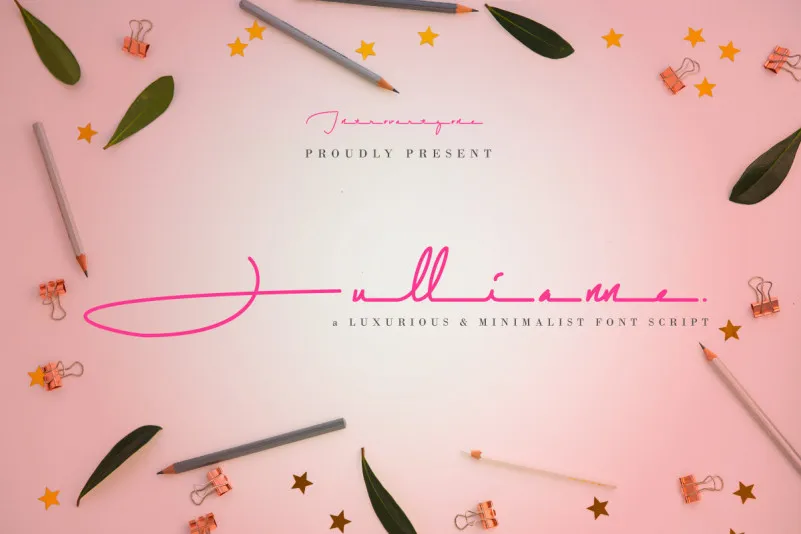
Jullianne Script Font – Download Grátis
A fonte Jullianne Script é uma combinação encantadora e minimalista para seus projetos digitais. Suavemente luxuosa e marcada por sua elegância monolineária, esta font é perfeitamente adaptada a um amplo espectro de aplicações designísticas. Ideal tanto para os designers que querem dar um toque pessoal em suas marcas como também para aqueles que precisam de um design minimalista para invocar uma atmosfera elegante e sofisticada. Este conjunto não apenas é versátil, mas também pode ser usado em várias situações, desde criação de convites para casamentos e design gráfico até a produção digital. É uma escolha perfeita para qualquer designer que deseja adicionar um toque único às suas criações, seja através do uso como marca d’água ou da criação de cartões de visitas personalizados. Seja você um artista digitais, designer gráfico ou criador de conteúdo online buscando dar um novo tom à sua identidade visual, Jullianne Script pode ser a fonte perfeita para atingir seus objetivos. Com seu design minimalista e luxuoso, esta font é uma ótima escolha para tornar o seu trabalho ainda mais único e atraente.